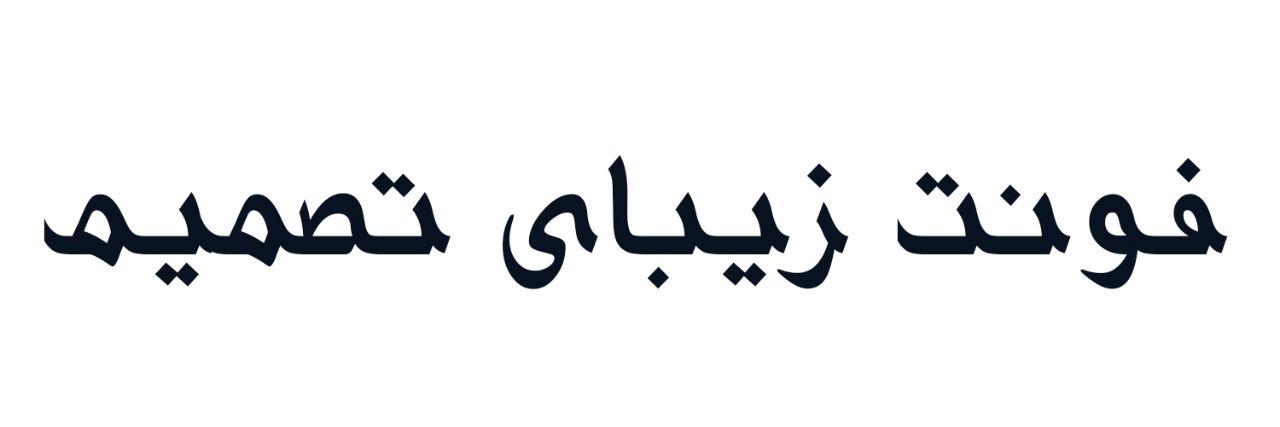
دانلود فونت تصمیم در خدمت شما بزرگورارن هستیم با ارائه فونت زیبا و فارسی تصمیم این فونت برای طراحی های لوگو و بنر و…. مورد استفاده قرار میگیرد.
ویژگی های فونت تصمیم :
• مدرن و کاربردی
• زیبا و خاص
• مناسب طراحی لوگو و بنر
تصاویری زیبا از طراحی های خاص با فونت مستند که برای نمایش و نمونه پیش فرضی از نمایش این فونت کاربردی طراحی شده است